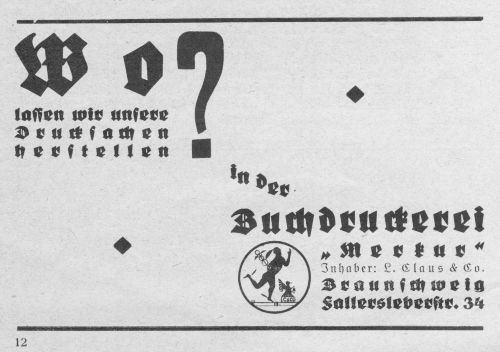
Mein Gott, bist du lustig …
Steht da nicht eigentlich in deiner Leseweise „Lecten Gie midj am Urfdj“?
Druckerei-Inserat von 1928
Auszeichnungs-Schrift: Wiking von Heinz König
Gießerei: Trennert und Sohn, Hamburg, 1925
Ist das nicht ein gutes Beispiel, dass diese Pflichtligaturen unsinnig sind?
Ohne Berücksichtigung des Fugen-lang-s würde es doch ›Brauns-chweig‹ heißen. Außerdem finde ich gerade in den gesperrten* Zeilen die Ligaturen als schwarze Flecken ziemlich störend.
Die Schrift an sich finde ich sehr schön – ich mag diese trapezartigen Stämme :biglove:
*) ... und war da nicht irgendwas mit Schafen und gesperrtem Satz mit gebrochenen Schriften!?
Ich würde mal sagen, dass es schlicht eine Frage der Gewohnheit ist, ob einem die Klötze der Pflichtligaturen im Sperrsatz stören oder nicht.
Damals waren diese ja allgegenwärtig, und wurden praktisch wie Buchstaben, wie z.B. das ja nicht minder dunkle, klotzige w empfunden.
Daher mochte ich darüber eben nicht richten, sondern empfinde es eben als richtiger, auch wenn diese Ecken und Kanten eben ein für heutiges Empfinden etwas raues Bild ergeben, nutzt man die alte Schrift, dass man auch die zu dieser Zeit gültige Schreibkonvention anwendet, nutzt man dagegen eine dem heutigen Formempfinden angepasste Schriftart, sollte man sich dann auch den heutigen Schreibregeln anpassen.
... und wartet dort auf Wiederbelebung die Tage irgendwann.
Ich kann ja mal schauen, ob ich auf der Belegung noch ein Eckchen frei habe für UNZ-Ligaturen etc. im PUA ;-)
Die Beschriftungsfrage ist immer noch offen, ich grüble gerade, ob ich mir irgendeine pinselfreie Lösung einfallen lassen sollte ...
Evtl. stelle ich die dann, wenn fertig, auch mal hier rein.
Schaurig schön!
Meine Tante arbeitete jahrelang in einem Blumenladen im U-Bahnhof Alexanderplatz, einen Kilometer entfernt vom nächstgelegenen Teil der Mauer. Wegen ihr war dieser Ort für mich immer ein Fixpunkt in dem verwinkelten S- und U-Bahnhof, auch nachdem sie schon längst nach Spandau „umgezogen“ war. Ich meinte eigentlich, diesen Ort, an dem ich mehrmals die Woche vorbei kam, wie meine Westentasche zu kennen. Was habe ich gestaunt, als Ende ’89 nur Zentimeter neben „ihrem“ Landen, statt der langen Wand, die dort scheinbar schon immer gewesen war, plötzlich eine Treppe zum Bahnsteig der bis dahin ausschließlich Westberliner U-Bahn war! :-o